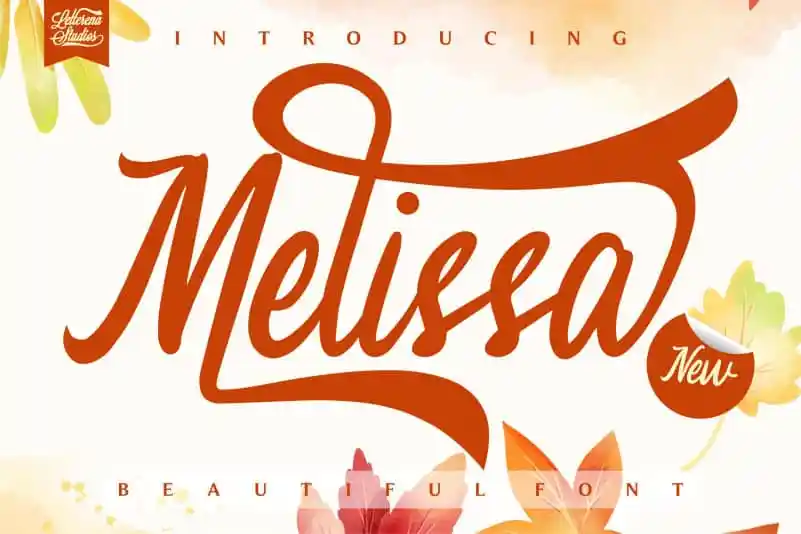
Melissa – Script Font – Download Grátis
A fonte “Melissa – Script Font” é uma elegante escolha para aqueles que desejam adicionar um toque autêntico à suas criações digitais e impressas. Criação de um designer chamado letterenastudios, essa fonte script é projetada com um pincel sofisticado, resultando em linhas fluidas e autênticas. Suave o suficiente para textos legíveis, mas forte o bastante para destacar elementos importantes ou dar vida a mensagens digitais. Seja você que está criando cartões de apresentação, projetos visuais, arte digital ou até mesmo cartazes, Melissa – Script Font é ideal. Sua versatilidade permite incorporá-la em um amplo espectro de usos e finalizações gráficas. Experimente Melissa e descubra uma fonte que combina com seu próprio estilo.